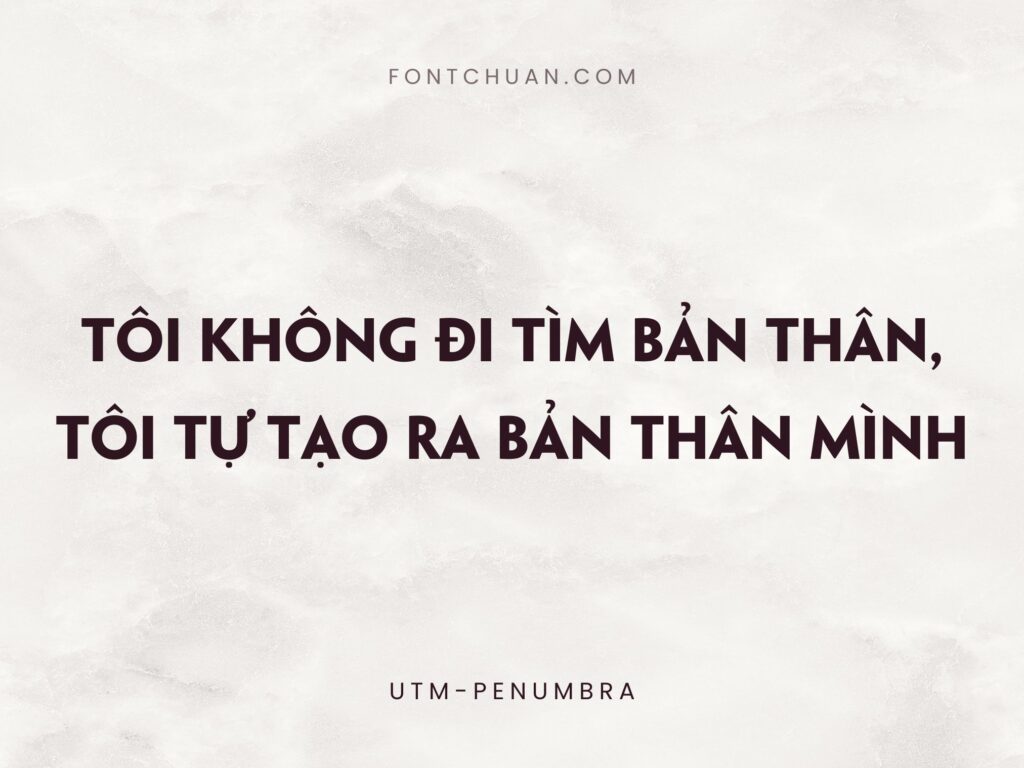
UTM Penumbra là phiên bản Việt hóa của font chữ Penumbra, một kiểu chữ sans-serif được thiết kế bởi Lance Hidy và phát hành bởi Adobe. Font này nổi bật với các ký tự in hoa có đường nét đậm, góc cạnh rõ ràng, tạo cảm giác mạnh mẽ và hiện đại. Phiên bản Việt hóa đã được thực hiện bởi Công ty TNHH Vitoen, hỗ trợ đầy đủ tiếng Việt cùng hơn 100 ngôn ngữ khác. Đây là một trong những font được cộng đồng thiết kế sưu tầm và chọn lọc nhằm đáp ứng nhu cầu đa dạng trong thiết kế.
UTM Penumbra có cấu trúc chữ với các nét thẳng và cong hài hòa, tạo nên sự cân đối và dễ nhìn. Font này phù hợp cho các ứng dụng như thiết kế tiêu đề, logo, bao bì sản phẩm và các ấn phẩm in ấn yêu cầu sự mạnh mẽ và chuyên nghiệp. Các ngành nghề như quảng cáo, giáo dục, công nghệ và bất động sản có thể tận dụng UTM Penumbra để tạo điểm nhấn độc đáo trong thiết kế.